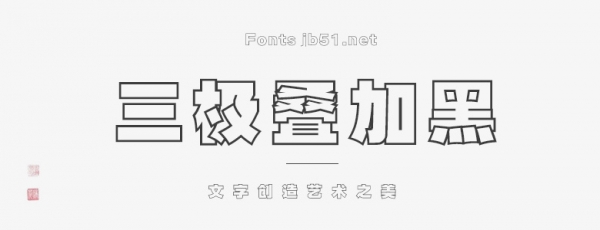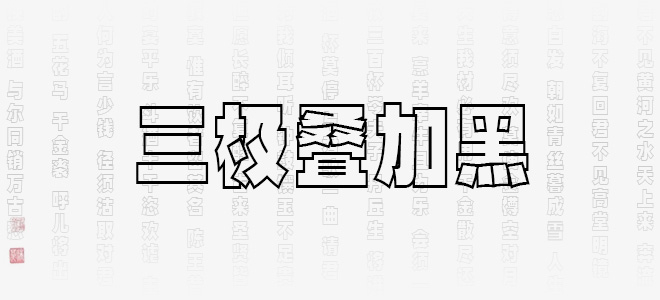
三極疊加黑用筆畫疊加的形式展現(xiàn)字體風(fēng)格,字形清新,結(jié)構(gòu)嚴(yán)謹(jǐn),布白均勻,重心一致。適用于各類便攜式屏幕的系統(tǒng)嵌入字體,以及傳統(tǒng)印刷媒介的標(biāo)題與正文排版。在品牌形象設(shè)計中作為logo設(shè)計性文字視覺效果更佳。
三極疊加黑